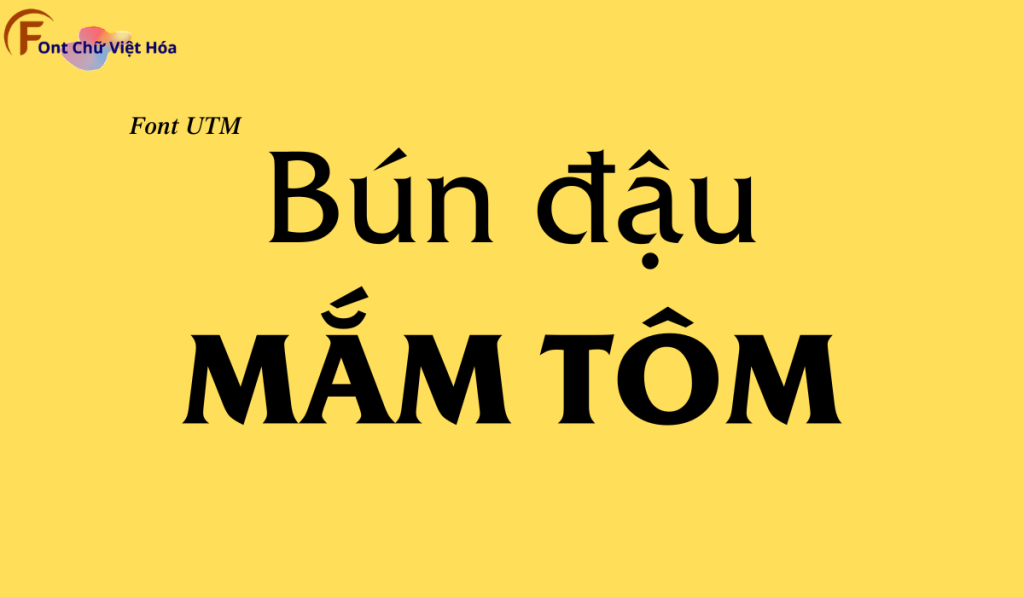
Font UTM God World Việt Hóa
Phân loại: Cá tính, Độc đáo
Kiểu chữ: Chữ không chân
Font UTM God World Việt Hóa là một font chữ có chân sang trọng, thuộc bộ font UTM. Được thiết kế với mục tiêu mang lại sự quý phái và đẳng cấp, font này lý tưởng cho các dự án thiết kế như thiệp cưới, bìa tạp chí, và các sản phẩm cao cấp. Với các nét chữ thanh mảnh và độ dày đều đặn, Font UTM God World Việt Hóa không chỉ dễ đọc mà còn tạo cảm giác tinh tế và đẳng cấp. Việc Việt hóa font giúp người dùng dễ dàng tích hợp vào các thiết kế tiếng Việt, mang lại sự tiện lợi và nâng cao tính thẩm mỹ.